字体一:逐浪海棠居刻本字
逐浪海棠居刻本字是一款仿古的刻本文字,以楷书为表现形式。勾画,最后收笔上平,尖点切去锐角,符合雕版制作工艺风貌。横竖交接处,有较尖锐的隼卯结构。细横,较参照字粗两个单位。多有切角,每字有1-2笔又保留尖角。求平和,不要陡峭,有传世其它刻本字,多有勾处收笔峭峻逼人。此乃良字也。
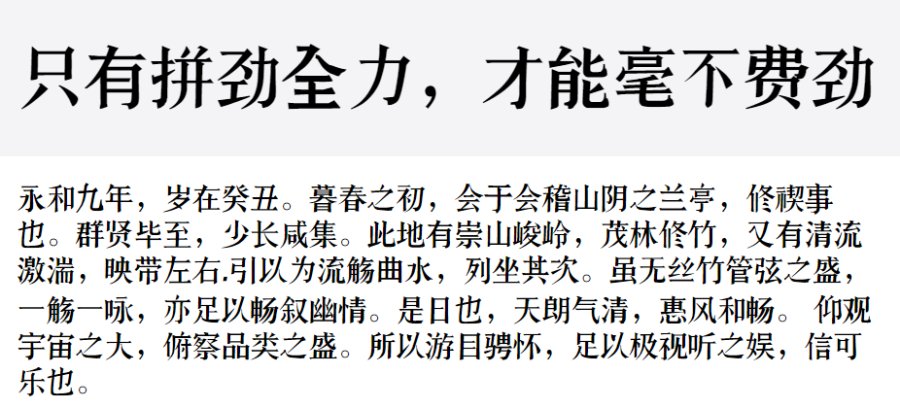
字体二:上首战戟体
上首战戟体,简体中文约6763字,字体笔画奇特,取自战戟的轮廓,横竖笔划增加了突出的尖角以及曲线,整体字形雅正,具有稳重沉稳的风格。
字体三:逐浪雅宋体
逐浪雅宋体是一款专门为平面设计行业量身打造的一款字体,这款字体不仅整洁大方、时尚美观,最关键的是加入了现代美术的元素,给人的第一感觉就是艺术气味浓郁,字体之间到处布满着艺术气息,这类字体广泛适用于广告设计,平面设计,报纸杂志等。